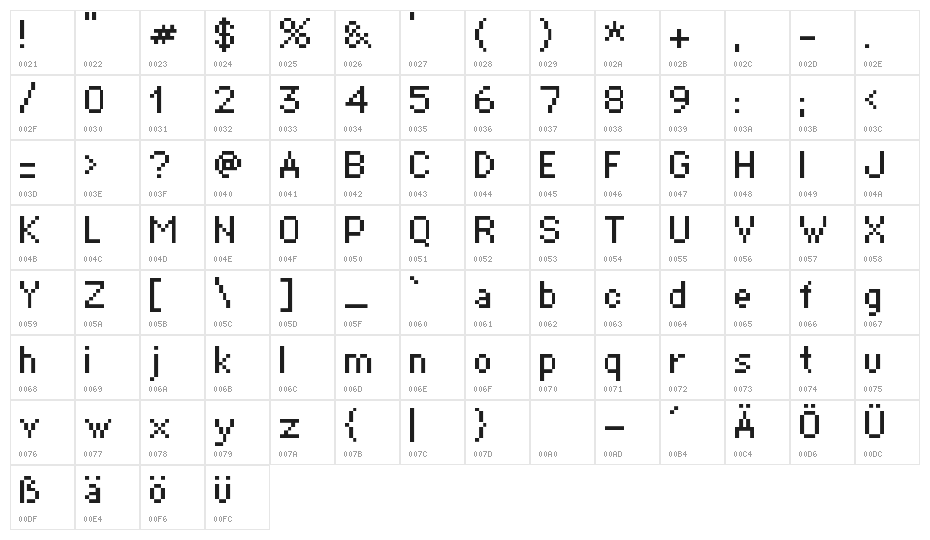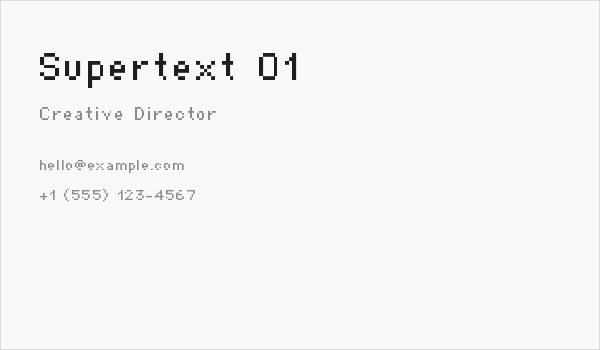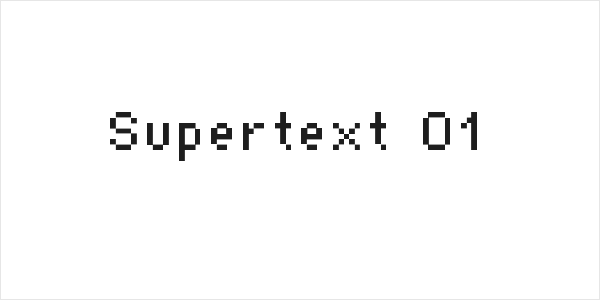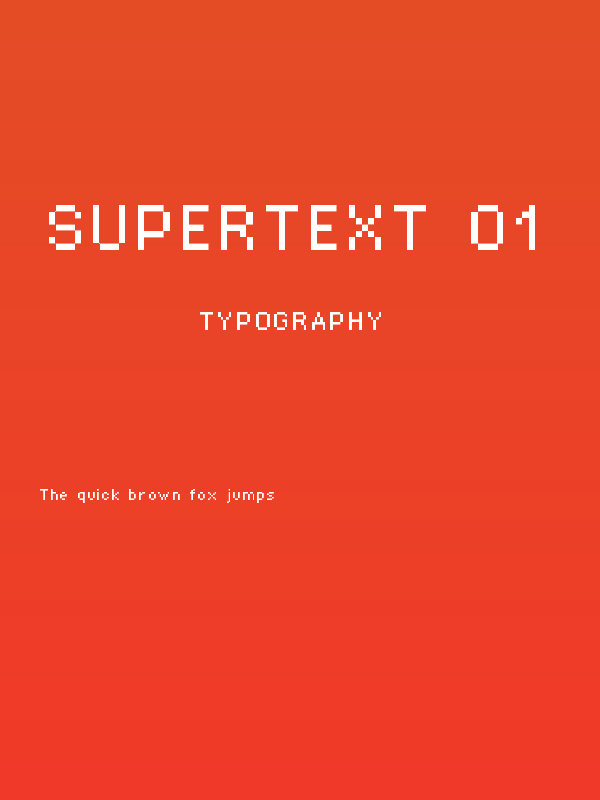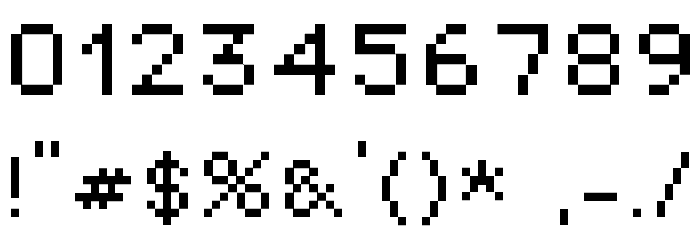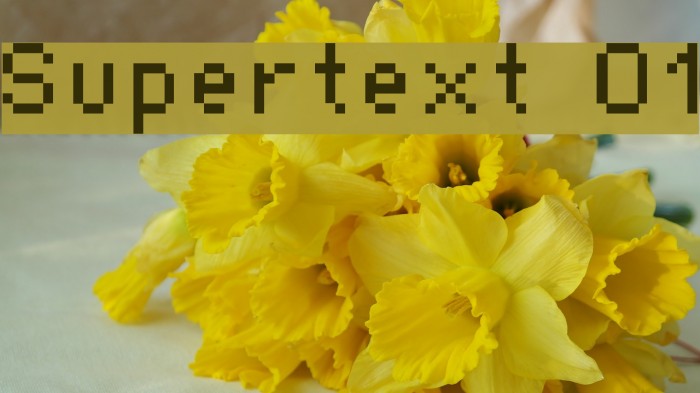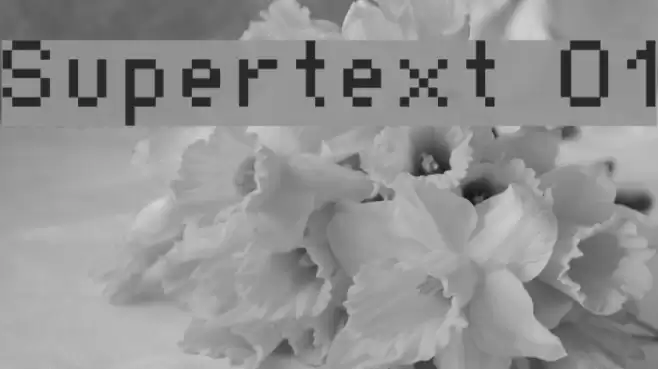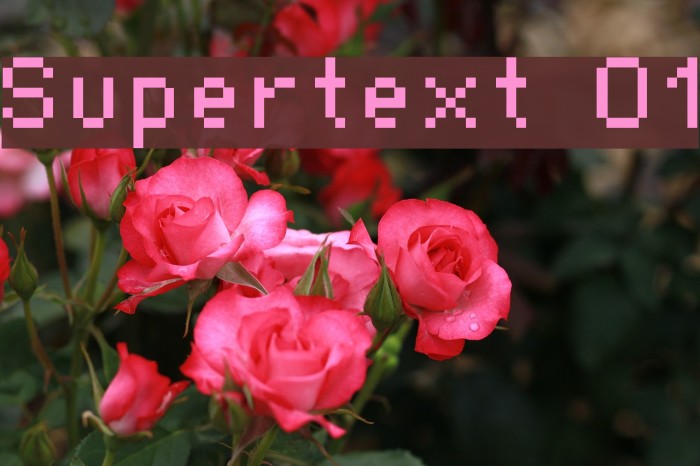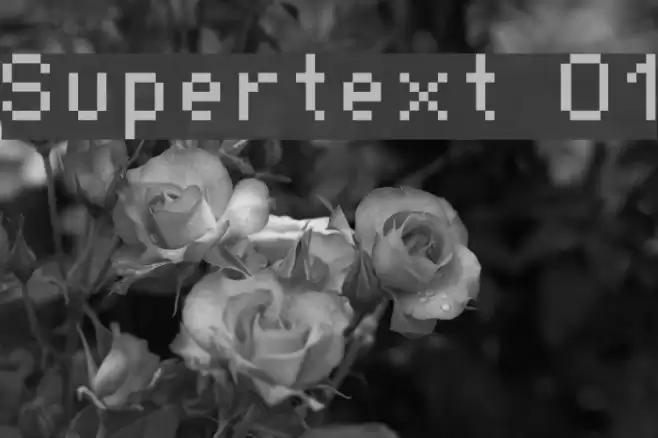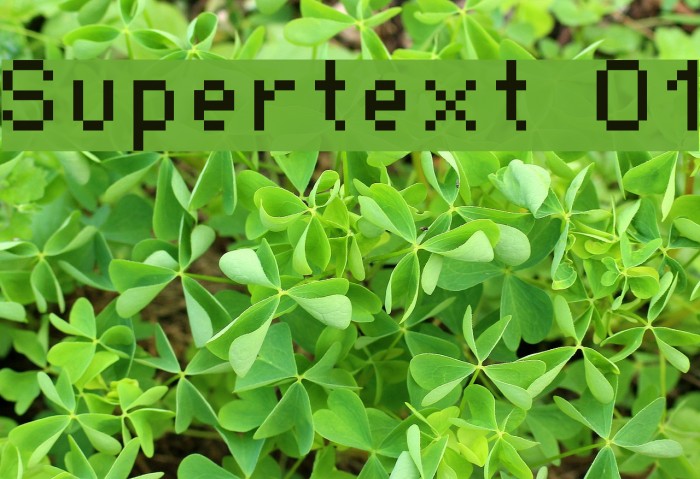
Supertext 01 Font
| समग्र शैली | Vintage |
| उपयोग का मामला | Headlines, Logos, Digital Art |
| सुझाए गए प्रोजेक्ट | Ideal for projects involving retro video games, digital art, tech-themed designs, or any creative work that seeks to evoke nostalgia for early computing. |